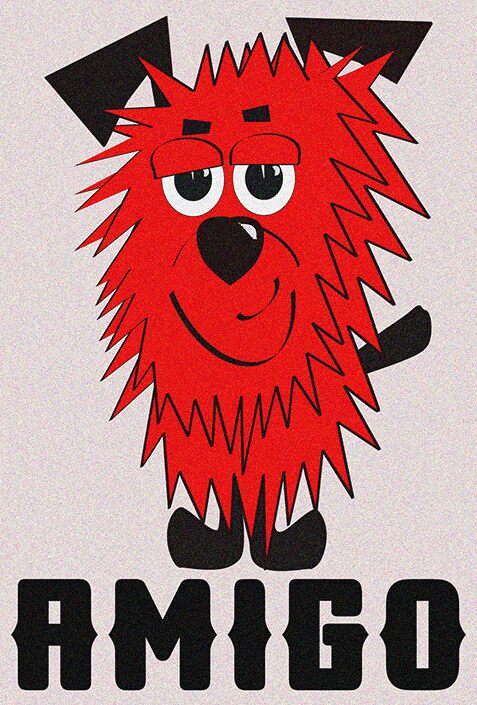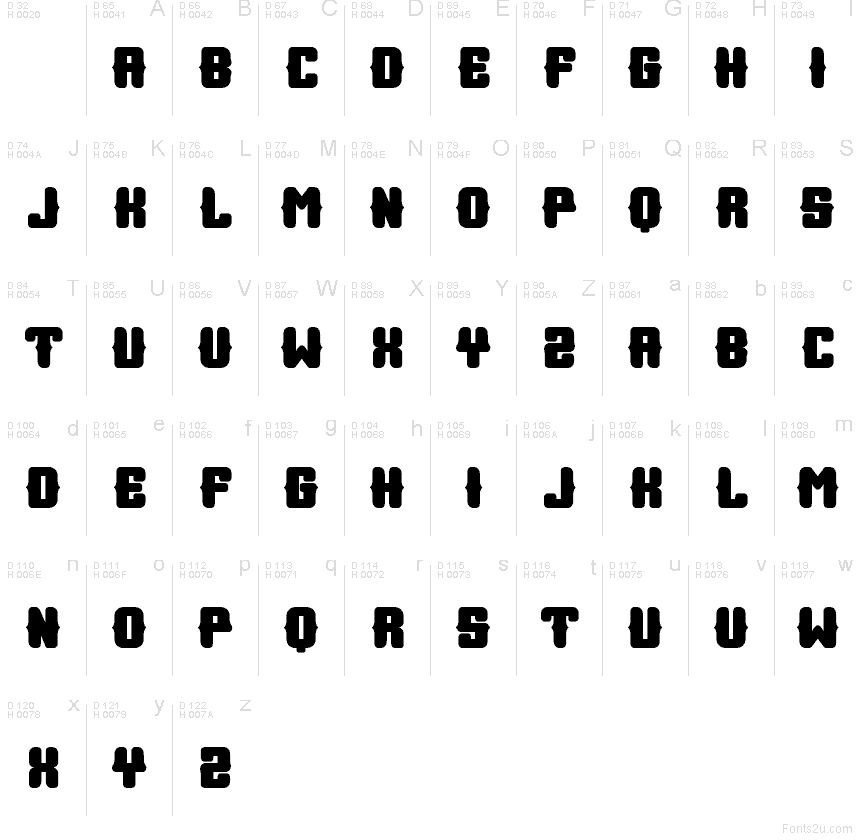
Amigo Extravagant od Vladimira Nikolica je bezplatné mexické displejové písmo s robustními verzálkami, zaoblenými rohy a vykrojenými středy, které písmenům dodávají vyřezávaný, festivalový nádech. Tvary jsou široké a výrazné, ale díky měkkým křivkám působí přátelsky a rytmicky.
Přirozeně zapadne do identity restaurací, menu taco bister, festivalových plakátů, obalů alb nebo krátkých titulků na obalech, kde je potřeba ručně malovaný, výrazný styl bez přílišné syrovosti. Díky kompaktní a husté sazbě verzálek skvěle funguje také pro titulní karty, nadpisy a monogramy, které potřebují spíše silnou siluetu než jemné detaily.
Amigo je dostupné ve dvou řezech: Regular a Rustique.